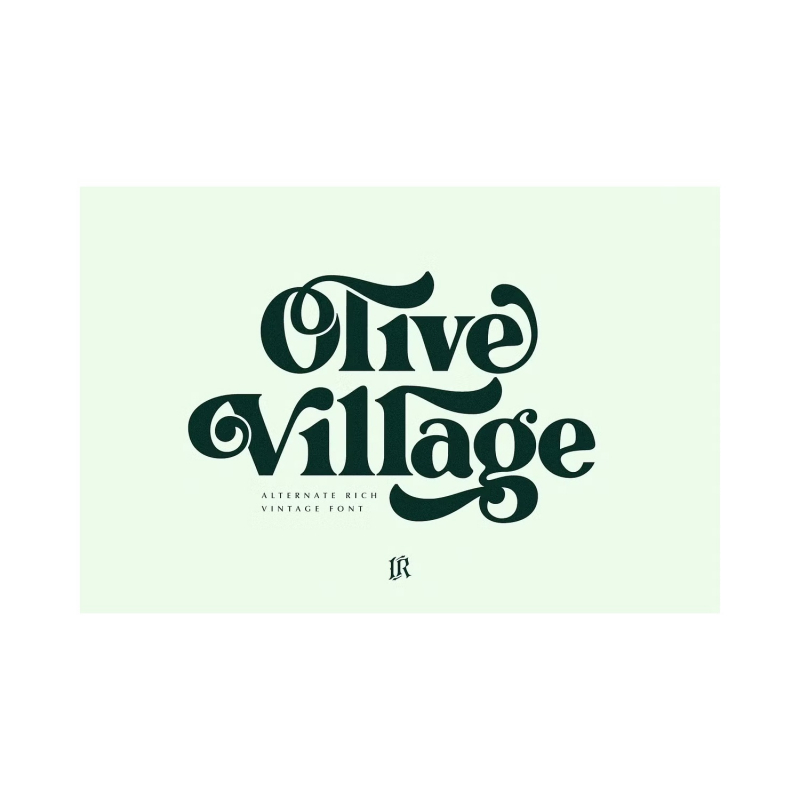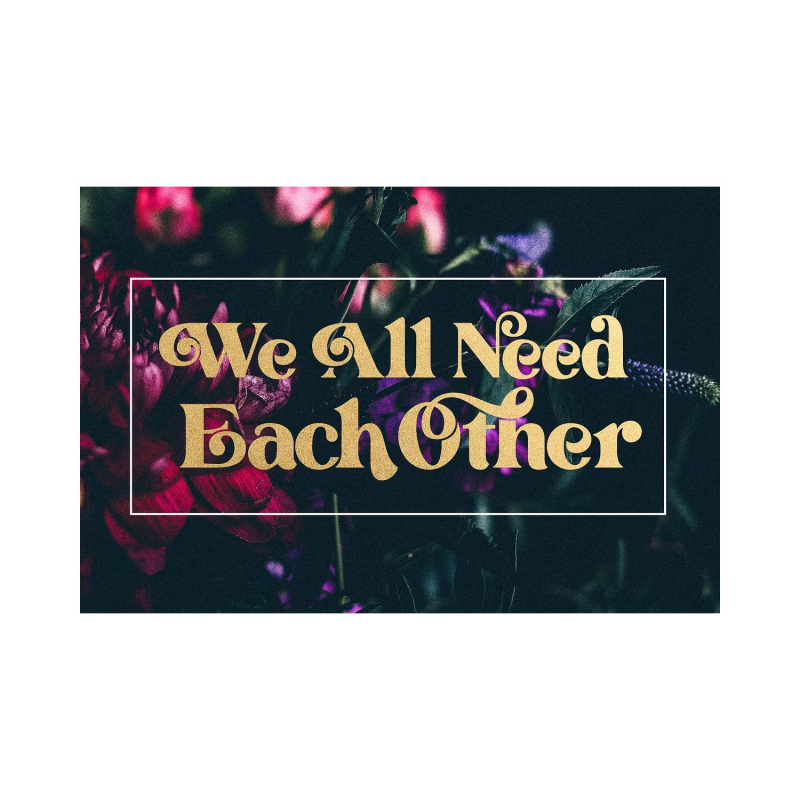
أوليف فيليدج - فينتاج فونت
• الاصدارات : عادي ومائل
أوليف فيليدج هو خط عتيق أنيق مستوحى من أجواء 70 الرائعة مع لمسة من الحداثة. يبدو مذهلا في أحجام العرض ويمكن قراءته بسهولة في حجم النص. تأتي Olive Village مع إمكانية الوصول إلى ميزات OpenType الخاصة بك ، ومجموعة كبيرة من الحروف الرسومية والأحرف المركبة البديلة. هناك نسختان من هذا الخط: عادي ومائل.
Olive Village هو خط عرض مصمم بشكل أساسي للعناوين والنصوص القصيرة الأخرى وهو مناسب تماما للإعلان ولوحة المزاج القديمة والعلامات التجارية والشعارات والتغليف والعناوين والتصميم التحريري والتصميم الحديث والعتيق.